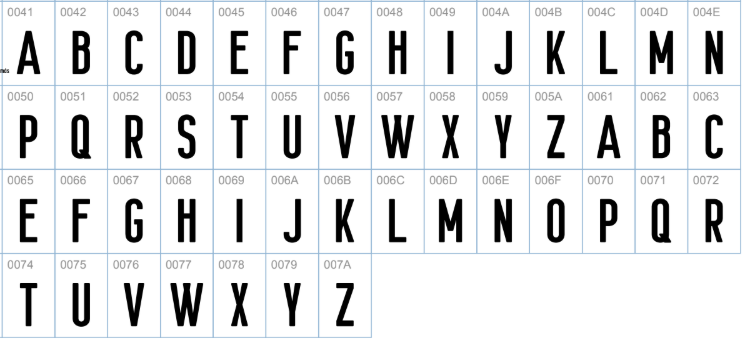
A identidade visual do Esporte Clube Bahia é uma das mais fortes e consolidadas do futebol brasileiro, especialmente através da a Puma. Para a temporada 2025/26, o “Tricolor de Aço” manteve a tradição de apresentar uniformes que unem a história do clube à modernidade exigida pelo Grupo City, trazendo uma tipografia exclusiva que reflete a força da torcida baiana.
Estilo visual da tipografia
A fonte desenvolvida para a temporada 2025/26 do Bahia reflete o momento de profissionalização e expansão internacional da marca. O design foge do padrão genérico, apostando em traços que equilibram a robustez necessária para números de camisa com a elegância das curvas.
• Design e Legibilidade: A tipografia possui características geométricas claras, com pesos (espessura) bem definidos que facilitam a leitura à distância. É uma fonte sans-serif moderna, ideal para aplicações em fundos listrados (como na camisa 1) ou sólidos.
• Identidade Tricolor: Diferente de fontes retrô, este estilo busca uma comunicação direta e contemporânea. Em muitas aplicações, ela inclui detalhes sutis nos ângulos que remetem às pontas da bandeira ou à dinâmica de movimento.
• Aplicação: Nos uniformes oficiais da Puma, a fonte é geralmente aplicada em cores contrastantes (azul ou vermelho sobre branco, e branco ou dourado sobre a camisa tricolor), muitas vezes acompanhada de contornos (strokes) para garantir o destaque sobre as listras verticais.